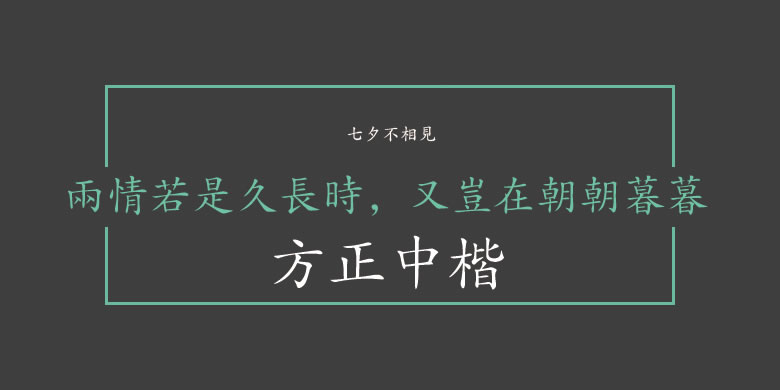
字体介绍 品牌:方正字库设计师:方正字模部发行时间:1996字库编码:大陆繁体(GB12345-90)、港台地区(BIG-5)分类:楷体 英文名称:FZZKFW.TTF 方正中楷的风格与方正楷体一致,且采用台湾笔形,只有繁体字库。这款字体字形端正严谨,笔画平直,布白均匀,适用于各类报纸、杂志和书籍中的正文。方正中楷的BIG5封装版本是专门针对港台用字的。使用GB12345-90封装的版本要留意文本校对。 字体下载 官方下载